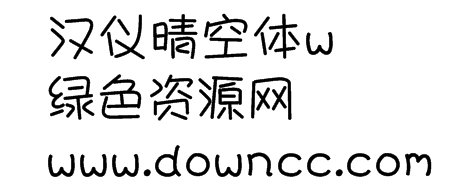
漢儀晴空體w是在漢儀晴空體的基礎上的完善版本,字庫更加完整,能滿足更多的設計需求,風格模板上并未有大的改動,需要的朋友就來綠色資源網試試吧!
漢儀晴空體簡是一款具有手寫POP風格的卡通字體,該字體俏皮可愛,趣味實足,非??ㄍ?。適合應用于廣告設計、名片設計、包裝印刷、產品設計等應用。
漢儀晴空體是一款非常好看的藝術字體,常用于photoshop相關的平面設計,在一般的瀏覽器、閱讀器、辦公軟件中,漢儀字庫特別為廣大文藝青年準備了“年味”十足的古風書法字體,把地道的中國風帶給大家。